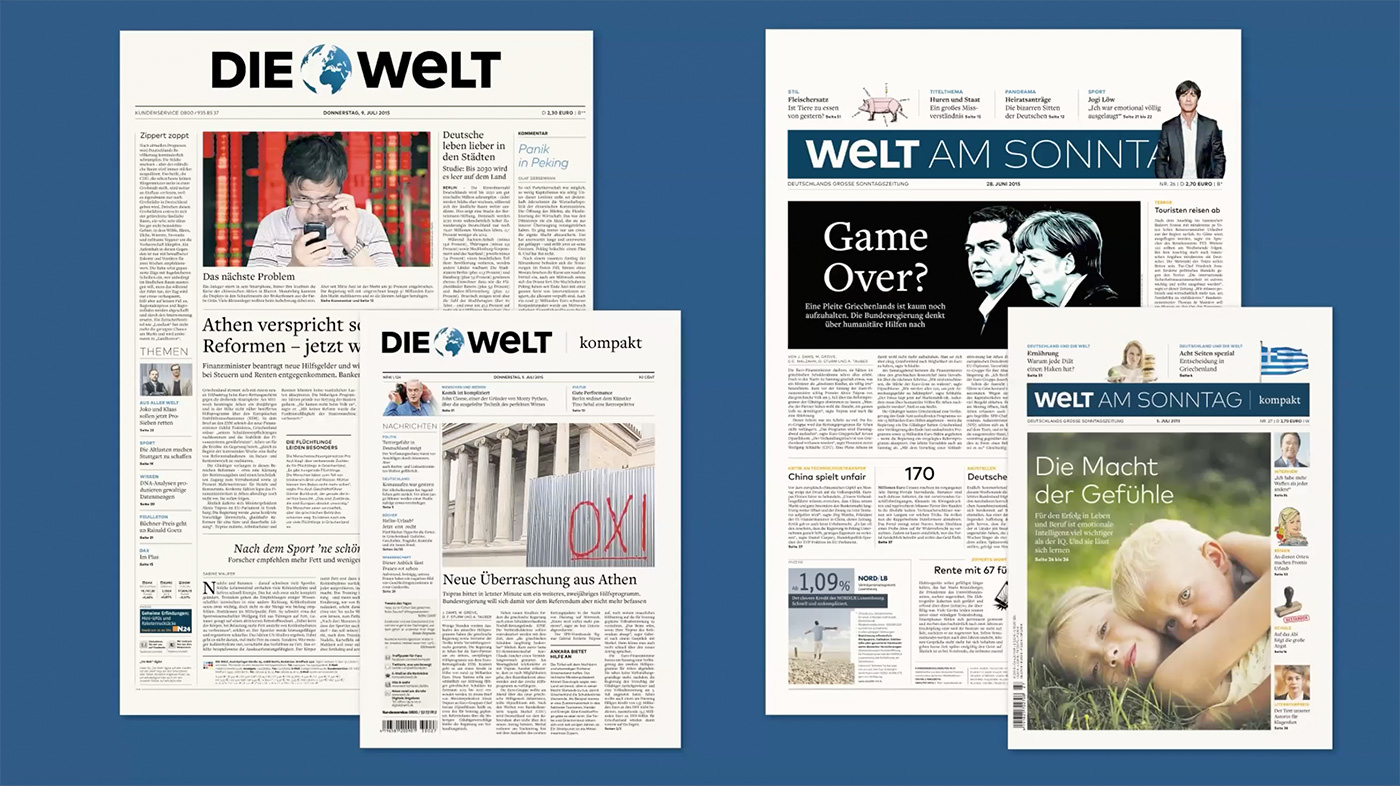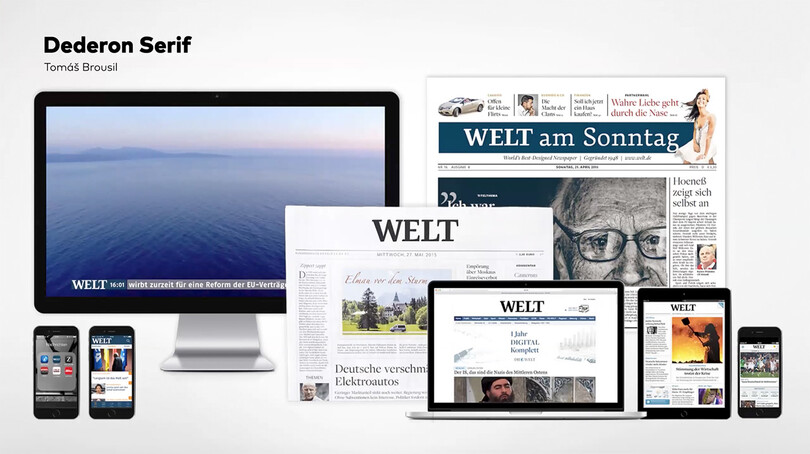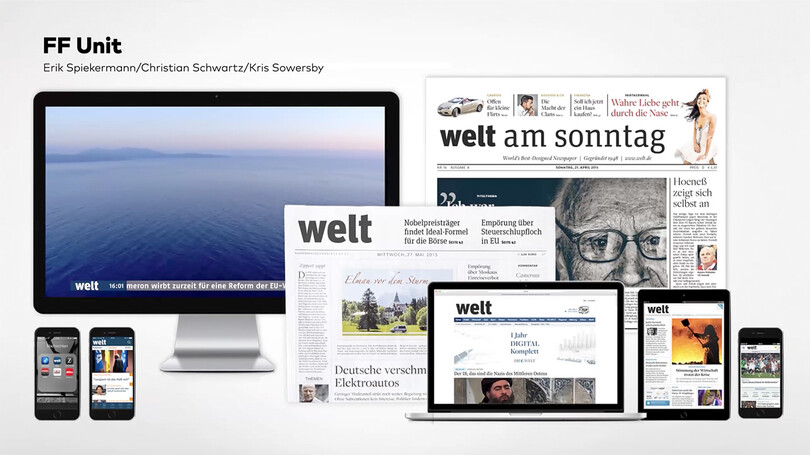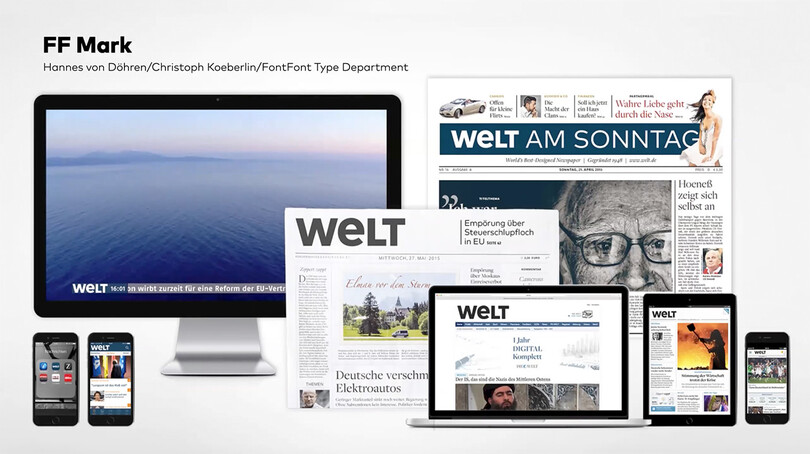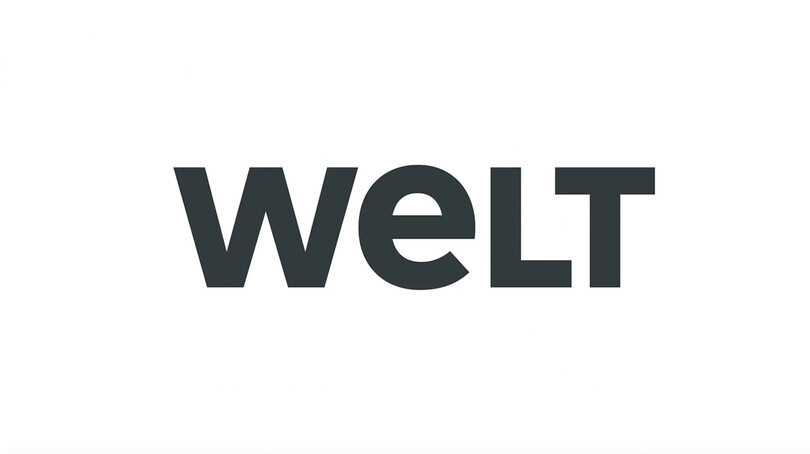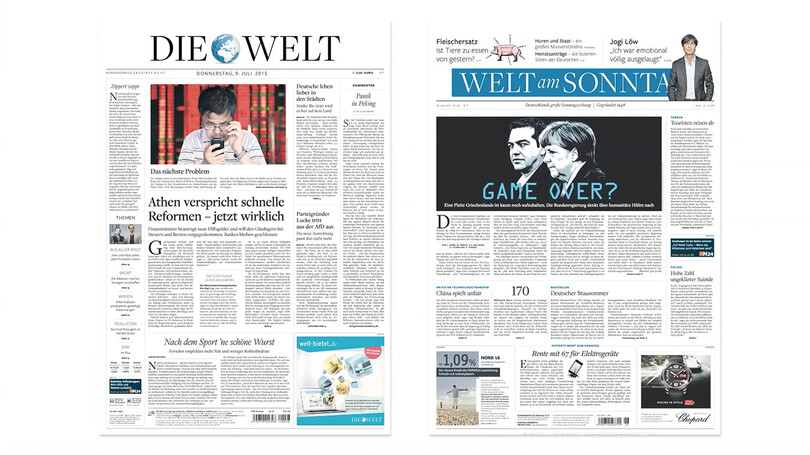
コーポレートブランディングと書体選定について
グラフィックデザイン・書体デザイン・出版関係と幅広く活動されている出雲利弥(いずも・としや)氏のプレゼンテーション。出雲氏は早稲田大学社会科学部卒業後、ドイツに留学。ベルリン芸術大学のビジュアルコミュニケーション学科を修了し、10年以上ベルリンのエーデンシュピーカーマンで、タイポグラフィ、コーポレートフォント、ピクトグラムのスペシャリストとして勤務。
エリック・シュピーカーマン氏について
エリック・シュピーカーマン氏は、出雲氏が卒業した大学の教授で、勤務先企業の創業者。世界的に有名なドイツ人タイポグラファ、デザイナーで、コーポレートブランディングの世界で書体デザインとタイポグラフィの重要性を長年説いてきた方です。書体デザイナー、本の著者、教育者、起業家としても成功を収め、講演やデザイン賞の審査で世界中を飛び回っていました。シュピーカーマン氏が作った書体で有名なのは、FF MetaやITC Officinaです。
エーデンシュピーカーマンについて
エーデンシュピーカーマンは、デザインコンサルタント企業として、デザイン戦略、ブランドコンセプトの立案、企業への導入などを手助けするデザイン会社。タイポグラフィをデザインの基礎として、企業の問題を解決できるような助言を行っています。ベルリンが本拠地で、ロサンゼルス、アムステルダム、シンガポールなどにも支店があります。
ドイツ鉄道の専用書体開発では、すべての印刷物やコーポレートブランディングに利用される書体が一から制作されました。見出し用書体と本文用書体、コンデンスト、コンプレスト、そのほかセリフ書体も含めた合計34種類のスーパーファミリーで、当時のコーポレートデザインすべての需要に対応しています。
また、ドイツの自動車部品・電動工具メーカー、ボッシュでは、10年以上にわたり、ロゴ、印刷物、パッケージング、ウェブサイト、社内外コミュニケーションに至るまで、あらゆる分野のコーポレートデザインをエーデンシュピーカーマンが担当しました。タイポグラフィと書体デザインをコーポレートデザインの中心に据えて、すべてのデザインを行っています。
Weltのリニューアル
Type&の講演では、コーポレートブランディングと書体選定の例として、新聞『Die Welt(ディー・ヴェルト、The Worldの意味)』のリデザインが紹介されました。ブランドの方向性、新しいロゴの提案、新聞、ウェブ、アプリ、テレビのレイアウトの提案までをエーデンシュピーカーマンが行い、その後、Welt社内でその他メディアにコンセプトを移植して運用するというものでした。
当時、ドイツの全国紙の新聞社「Welt」、ニュース番組局「N24」が合併することになり、新しいコーポレートデザインが必要になりました。それぞれのメディアがバラバラのデザインを採用していたため、これらをすべて統一し、同じコーポレートアイデンティティを持たせるのがプロジェクトの最終ゴールでした。
ドイツの全国紙では1位が『Süddeutsche Zeitung』(南ドイツ新聞)、2位が『Frankfurter Allgemeine Zeitung』、この2紙が圧倒的なシェアを持っていました。『Die Welt』は、売り上げでも販売地域でも2紙にだいぶ差をつけられて3位でした。Weltはすべてを刷新して、競合2社に追いつくよう、リニューアルすることになりました。
エーデンシュピーカーマンは最初にクライアント企業のトップたちとワークショップを行い、今後どうありたいのかを共有します。トップたちがバラバラの方向を向いていると、新しいブランドの方向性やデザインが決まりにくい。
次に、自社の強み弱み、競合他社の強み弱みを分析するために、この写真のようなボードを使って、業界内での自社の位置を冷静に分析します。そして、これらの分析から自社が未来にいくべき方向性を考えます。
この図では左がニュース、右が娯楽、下が事務的、上が感情的となっています。Die WeltとN24は最初左下のエリアにいました。今までは真面目なニュースメディアとして認識されていましたが、これからは真面目ではあるが、感情を表し、視聴者と同じ目線で会話するような方向に行きたいことを確認しました。
ワークショップで最終的に得られた結果は、「もっと読者と会話して感情を出さなければならない」「視聴者に愛されたり、嫌われたりすることをいとわない」「立ち位置を明確にし、もっと主張する」ということでした。そして、「新しいブランドWeltは、より感情を表に出し、立ち位置を明確にする。」という新しいスローガンを確認しました。
コーポレートフォントの選択肢
次に、ワークショップの結果がデザインに落とし込まれました。コーポレートフォント導入の方法として考えられるのが、まずリテールフォント、つまり既製品を買うということです。IKEAの家具のように、誰でもどこでも世界中で手に入るイメージです。すでに市場にある書体を買えば、一番安く誰でも同じ書体を所有できます。しかし、誰でも使用できるということは、ブランドのコモディティ化やオリジナリティの欠如、デザインの類似などの問題もあります。
2つ目はリテールフォントをカスタマイズする、これは例えば家のサイズに合わせて家具を調節するような感じです。すでにあるものに足りないものを補足したり、いらないものを取り除いたりできる利点がありますが、既存フォントをカスタマイズしようとすると、権利の問題があります。またリテールフォントを買うより、若干お金と時間がかかります。
3つ目は新しいフォントを作ること。フルオーダーメイドの家具のように、すべての詳細を設定して購入できる世界で唯一のものです。欲しいものがまだ存在しない、他社と差別化したい、自分の使用用途にぴったり合う書体が欲しい場合に合っています。新しく作るので、権利の問題がなく、ライセンス料や使用料も契約によってはかからず、いいこと尽くめのように思いますが、初期費用は一番高く、作る時間もかかります。
Weltの場合は、リテールフォントから書体が選ばれました。その理由は、予算と時間の都合、新聞業界の移り変わりの速さのため、そのデザインを何年使えるかわからないためとのことです。10年、20年たっても使えるオリジナルフォントを時間とお金をかけて作るより、見出しやロゴはリテールフォントから選び、本文では足りない言語や記号をカスタマイズして補うという構成で決定されました。
エーデンシュピーカーマンの場合、書体選定において、書体の背景、ジャンル、技術的な面など、よい書体をただ探し出して勧めるのではなく、常にそれが使用される状況を想定して適材適所に提案しています。書体の使われ方、レイアウト、一緒に使用される写真、グラフィック、またはメディアの違いや使用サイズの違い、文字が読まれる距離の違いなどによって、様々な可能性が考えられるそうです。
ロゴの提案
Weltのロゴリニューアルでは、以下の3案が提案されました。
1つ目は、Dederon Serif(デデロン・セリフ)。チェコ出身のトマス・ブロウシル氏が作ったオールドスタイル・ローマンの特徴を持った書体です。その特徴は、文字のストレスの傾き、手書きで書いた文字の特徴、低いコントラスト。大きなサイズでこのセリフ書体を使用すると、ダイナミックでクラシック、かつスマートで、なおかつ読みやすい。同じ特徴を持つサンセリフもあり、組み合わせてもマッチするように作られているので、見出しや他の場面にも使いやすい書体です。
2つ目は、FF Unit(エフエフ・ユニット)。エリック・シュピーカーマン氏とアメリカ人のChristian Schwartz(クリスチャン・シュワルツ)氏、のちにニュージーランドのKris Sowersby(クリス・サウスビー)氏が加わり、徐々に拡張されていったフォントです。サンセリフとスラブセリフ、角の丸いラウンデッド、それぞれ7種類のウェイトとイタリック、合計42書体があります。ヒューマニスト・サンセリフで、コンデンストという点はFF Metaと同じですが、手書きの特徴がなくなり、よりシンプルになります。明確でシンプルな現代的な書体です。
そして、3つ目がFF Mark(エフエフ・マルク)。Hannes von Döhren(ハネス・フォン・デーレン)氏とChristoph Koeberlin(クリストフ・ケベルリン)氏、FontFontチームによって作られたジオメトリック・サンセリフです。ジオメトリックとは、幾何学的形態のことで、FF Markは、そのジオメトリック・サンセリフを現代的に定義した書体です。11のウェイトとイタリック、ナロー、コンデンストまであります。この書体を伝統的なメディアである新聞に使用することは、とても大胆で、殻を打ち破るようなイメージです。
この3つの書体が提案され、最終的にFF Markに決定されました。「Weltは感情を表に出し、立ち位置を明確にする」という点に立ち返り、大胆でパワフル、実質的、誰にでもわかりやすい認識性のあるロゴ、現代的、革新的で他社と違うデザインなどがこのロゴから読み取れるというのが決定の理由でした。Weltの「e」だけ小文字ですが、とても感じよく、笑っている顔のようにも見えます。
紙面レイアウト
これは再デザイン前の紙面です。ロゴ、見出し、本文にセリフ書体とそのイタリック体を使用して、主張しない真面目さ、信頼感は伝わってくるかもしれません。しかし、この紙面から現代の読者はだんだん離れていきました。
こちらがリニューアルした新しい紙面です。本文用書体はFreight Text(フライト・テキスト)で、レイアウトも変更されました。見出しや本文には、セリフ書体、サンセリフ書体、大文字小文字、いろいろな組み合わせがあります。
まず新しいデザインで最も目を引くのは、ロゴの部分。すっきりして伝統的な紙の新聞ではないような印象です。ドイツでは、新聞の大半は駅や売店で販売されるので、同業他社と比べて一瞬で見分けがつくデザインが重要ということです。
また、見出しと本文は以前はすべてセリフ書体で組まれていましたが、新しいデザインでは、大きな見出しにセリフとイタリック体、中位の見出しにはセリフもサンセリフも使用されています。一見、統一感がなくなったように見えますが、レイアウトの階層性と書体の違いを利用して、読者のテンポを邪魔せずに、見出しから見出しに飛び回って目を引くような仕掛けが施されています。
『Welt am Sonntag』は日曜版なので、若干ページも増え、写真が大きくなり、雑誌のような紙面になりました。見出しはサンセリフで、その上にオレンジ色の全部大文字のアイキャッチとなる見出しがつけられています。
このように、メディアによってセリフとサンセリフの使い方が変更されています。紙の新聞ではセリフの使用が多めで、色の使用も控えめ。日曜版では少しサンセリフの使用が増え、ウェブサイトやアプリではサンセリフ書体の使用はさらに増えています。テレビでは、セリフ書体が取り除かれ、サンセリフのみでデザインされています。
出雲氏:以前のWeltは全部大文字のセリフ体だったので、権威的でクラシックで上から目線な印象がありました。新しいロゴは皆さんと同じような目線の高さで、柔らかい感じにしたいということで、丸いeをロゴの中に挟み込んだのです。
小林:プレゼンテーションの中で出雲さんが「eがちょっと笑っているような」という表現をされましたが、例えばeのデザインはHeineken(オランダのビール醸造会社、ブランド)のロゴのようなeもありますよね。
出雲氏:ここまでいくと、大笑いしている感じになってしまうんですよね。Weltはニュースメディアなので、真面目な方向性を出しながら、ちょっと微笑むぐらいの笑顔ですね。
小林:ドイツ鉄道のコーポレートフォントも結構革新的だったと思うのですが、決断の時にもう少し革新的な方向に行きたいというクライアントの意思があったのでしょうか?
出雲氏:当初は、昔のいい文字を改刻するという方向性で、若干地味な感じから始まりましたが、未来に向けてもう少し特徴的で、誰も見間違えないフォントが欲しいということで、徐々に方向性を変えていきました。